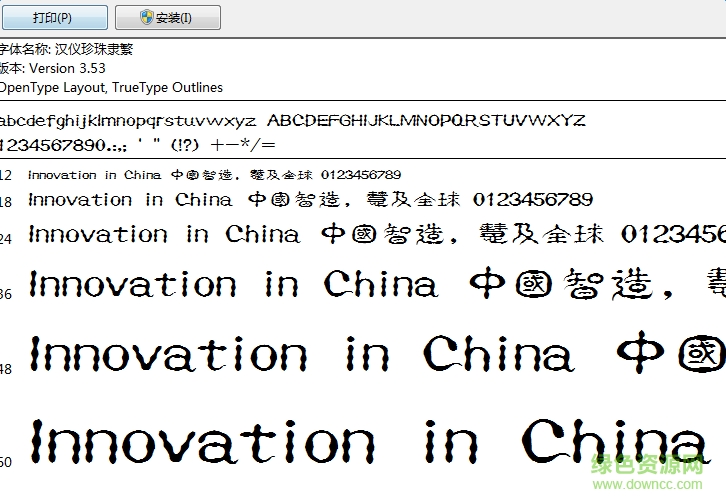
漢儀珍珠隸繁字體是一款漢儀字體庫中的個性字體,該字體可以廣泛應(yīng)用于廣告設(shè)計、宣傳海報、ppt、影視制作以及任何使用文字的領(lǐng)域,有需要的朋友可以免費(fèi)下載收藏。
漢儀珍珠隸繁字體是極具個性的漢儀字體,該字體以隸書為原型設(shè)計,整體效果非常出色,極具個性。有喜歡的朋友可以來綠色資源網(wǎng)下載使用!